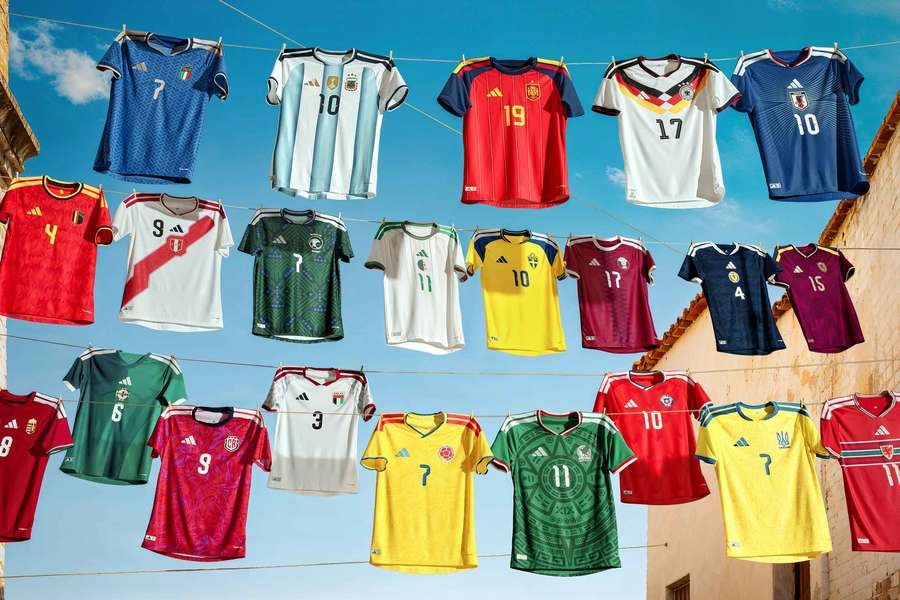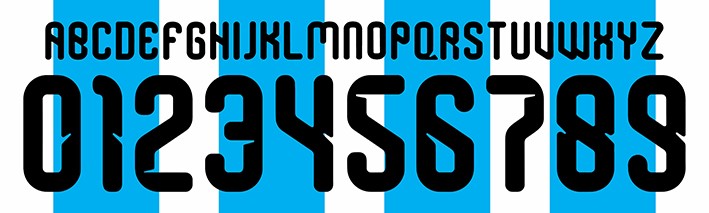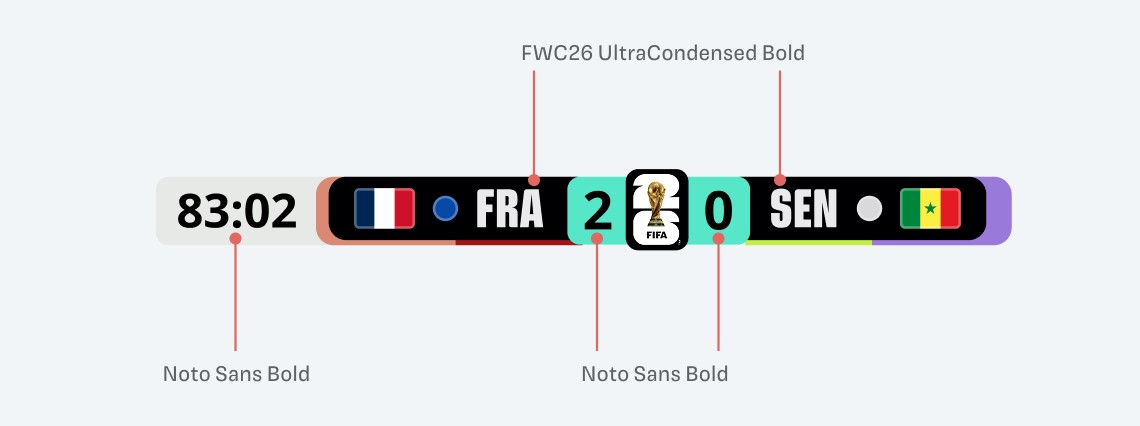
Mundial 2026: cuando la tipografía también sale a la cancha
Detrás de cada camiseta hay una decisión de diseño
Cuando pensamos en una Copa del Mundo solemos imaginar goles inolvidables, estadios repletos y camisetas icónicas. Sin embargo, para quienes trabajamos en diseño gráfico, impresión e identidad visual, hay otro protagonista que muchas veces pasa desapercibido: la tipografía.
Los nombres y números que vemos en las espaldas de los jugadores no son simples caracteres. Cada uno fue diseñado para transmitir identidad, representar la cultura de un país y garantizar una lectura perfecta tanto en la cancha como en una pantalla de televisión.
El Mundial 2026, en Estados Unidos, México y Canadá, demuestra que el diseño tipográfico también juega su propio campeonato.
La FIFA tiene su propia tipografía… pero no aparece en las camisetas
Uno de los errores más comunes es pensar que todas las letras del Mundial pertenecen a una misma familia tipográfica.
En realidad, la FIFA desarrolló una fuente exclusiva denominada FWC 2026, destinada únicamente a la identidad visual oficial del torneo: logotipos, señalética, gráficas institucionales, piezas promocionales y comunicación digital.
Esta tipografía forma parte de la identidad oficial del Mundial y está protegida como propiedad intelectual, por lo que no puede utilizarse libremente en proyectos comerciales.
Entonces… ¿por qué cada camiseta tiene una tipografía distinta?
Porque la FIFA únicamente establece normas relacionadas con el tamaño, la ubicación y la legibilidad de los dorsales.
El diseño de las letras queda en manos de las marcas deportivas y de cada federación nacional.
Nike, adidas y Puma aprovecharon esa libertad para desarrollar sistemas tipográficos completamente diferentes, buscando representar la identidad de cada selección y reforzar la personalidad visual de sus camisetas.
Uruguay: una tipografía con casi cien años de historia
Uno de los diseños que más llamó la atención fue el de Uruguay.
Nike tomó como inspiración las inscripciones del histórico Estadio Centenario y el legado del primer Mundial de 1930 para desarrollar una tipografía de estilo Art Déco.
Los números presentan una línea central que divide cada carácter, logrando una estética elegante, moderna y al mismo tiempo profundamente vinculada a la historia del fútbol uruguayo.
Cada marca eligió un lenguaje visual diferente
Aunque todas respetan el reglamento FIFA, cada fabricante interpretó el diseño desde una perspectiva distinta.
Nike apostó por líneas rectas, geometrías fuertes y referencias históricas.
adidas eligió tipografías con inspiración retro y efectos tridimensionales que aportan profundidad.
Puma, en cambio, desarrolló diseños más suaves y orgánicos, priorizando la limpieza visual y la lectura a distancia.
Mucho más que letras: un recorrido por los idiomas del mundo
El Mundial también se convierte en una enorme muestra de diversidad tipográfica.
Aparecen caracteres que pocas veces vemos en América Latina:
• Ø
• Æ
• Å
• È
• Ï
• Ć
• Circunflejos
• Diéresis
• Apóstrofos
Cada uno obliga a los diseñadores a desarrollar familias tipográficas completas, capaces de respetar las particularidades de cada idioma sin perder coherencia visual.
Cuando un buen diseño también debe ser legible
No todo es estética.
Uno de los debates que surgió durante el Mundial estuvo relacionado con la tipografía utilizada en los marcadores de televisión y en las transmisiones oficiales.
Diversos especialistas señalaron que la fuente oficial FWC26, pensada para generar impacto visual en títulos y campañas, pierde legibilidad cuando se utiliza en tamaños pequeños.
Por ese motivo, en algunos elementos gráficos de las transmisiones se combinó con Noto Sans, una fuente mucho más clara para mostrar tiempos, resultados y estadísticas en pantalla.
Una lección para cualquier diseñador gráfico
El Mundial deja una enseñanza muy clara.
Una tipografía espectacular no necesariamente funciona en todos los soportes.
Lo que luce increíble en un cartel puede resultar difícil de leer en un celular.
Lo que funciona en una camiseta quizás no sea adecuado para una interfaz digital.
Y lo que impacta en un estadio puede perder eficacia en una transmisión televisiva.
El verdadero desafío del diseño consiste en encontrar el equilibrio entre personalidad, funcionalidad y legibilidad.
¿Se puede utilizar la tipografía oficial del Mundial?
La respuesta es no.
Conclusión
Más allá de los goles y las emociones, el Mundial 2026 confirma que el diseño gráfico también ocupa un lugar central dentro del espectáculo.